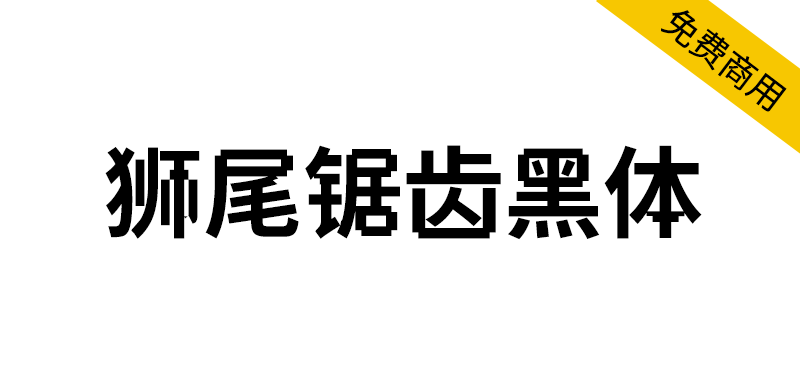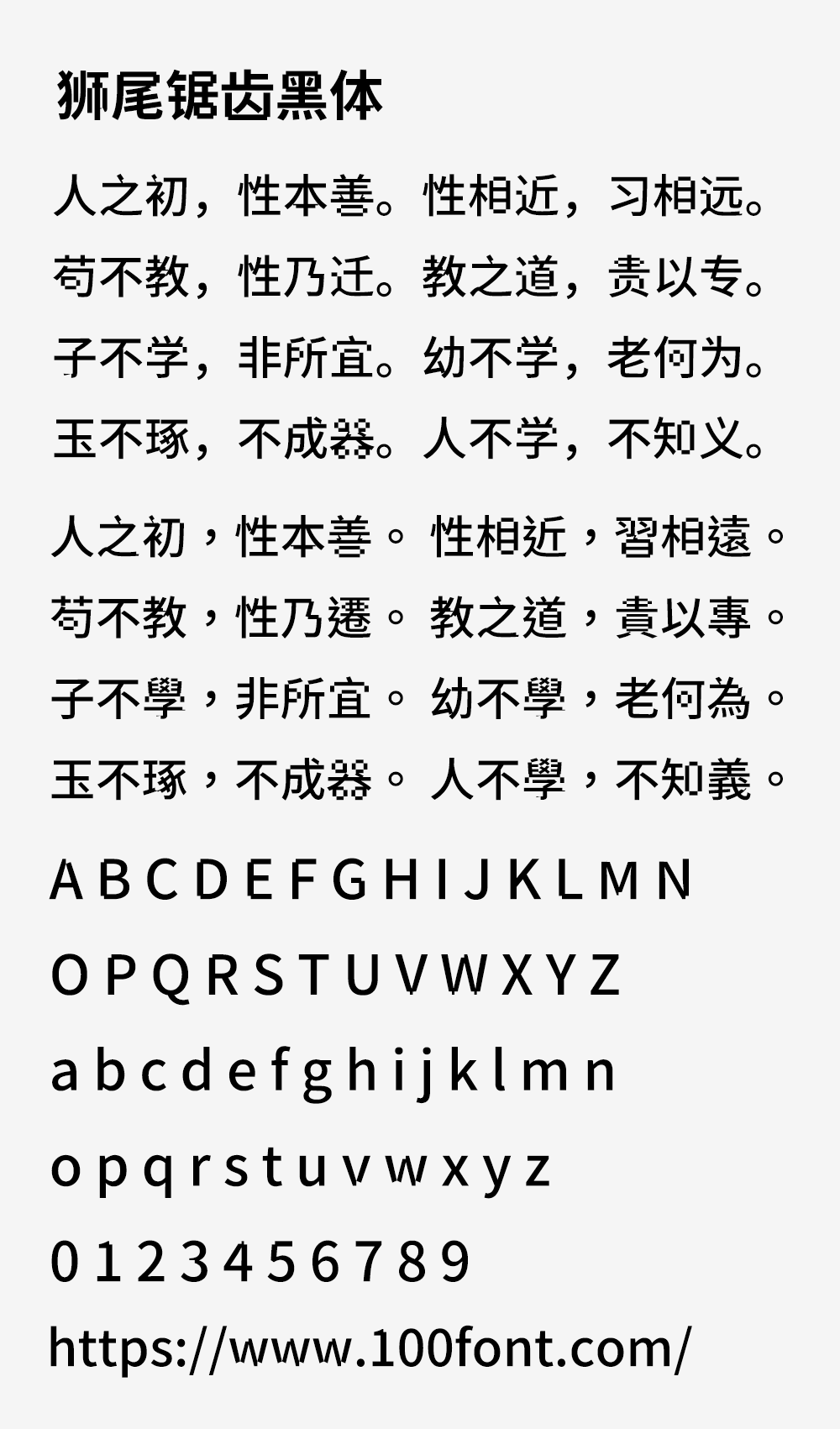
狮尾锯齿黑体基于思源黑体的转角挖空和拔脚改造,更加简明现代化的字体。狮尾锯齿黑体的特色是转角挖空,文字产生锯齿状的效果,有些文字没有处理的很好看,丑丑的。和思源黑体一样,有7种字重,支持简体中文、繁体中文、韩文与日文,可以免费商用,欢迎大家自由应用、自由优化、自由改作!
狮尾锯齿黑体与「狮尾锯腿黑体」差别在有没有拔脚,「拔脚」就是会有较少的笔画,例如移除「口」字的左右下角会多出的短线条。有拔脚的字会较圆,但是会造成有些字因直接去掉腿后左右不平衡、左右不对衬的「悬空」问题。改使用「腿」系列字体就不会有这个问题。